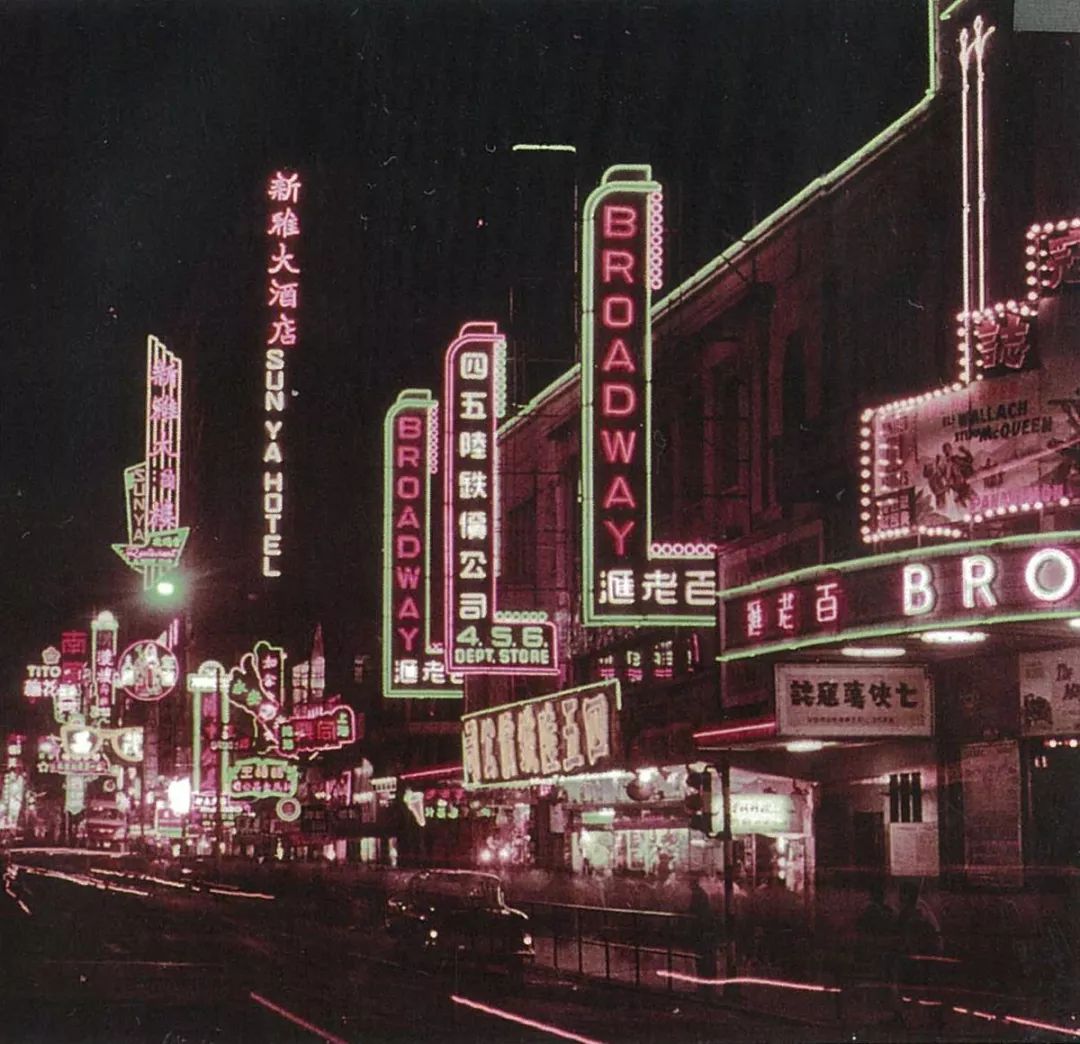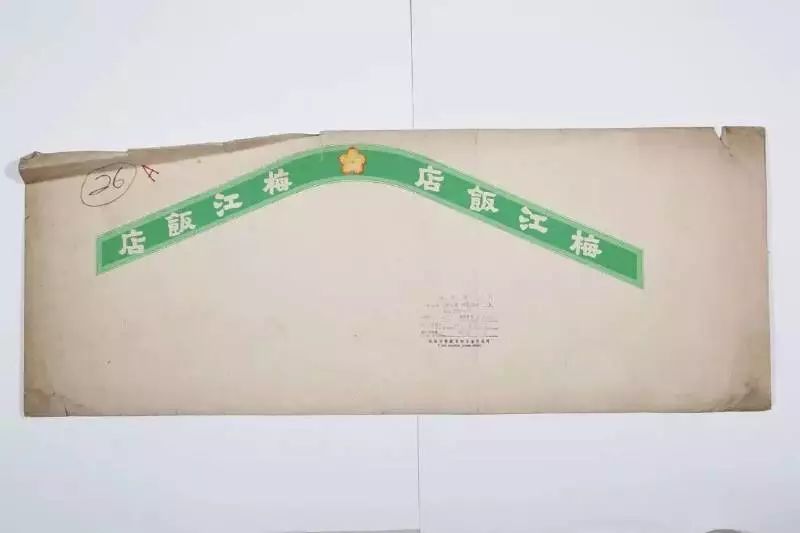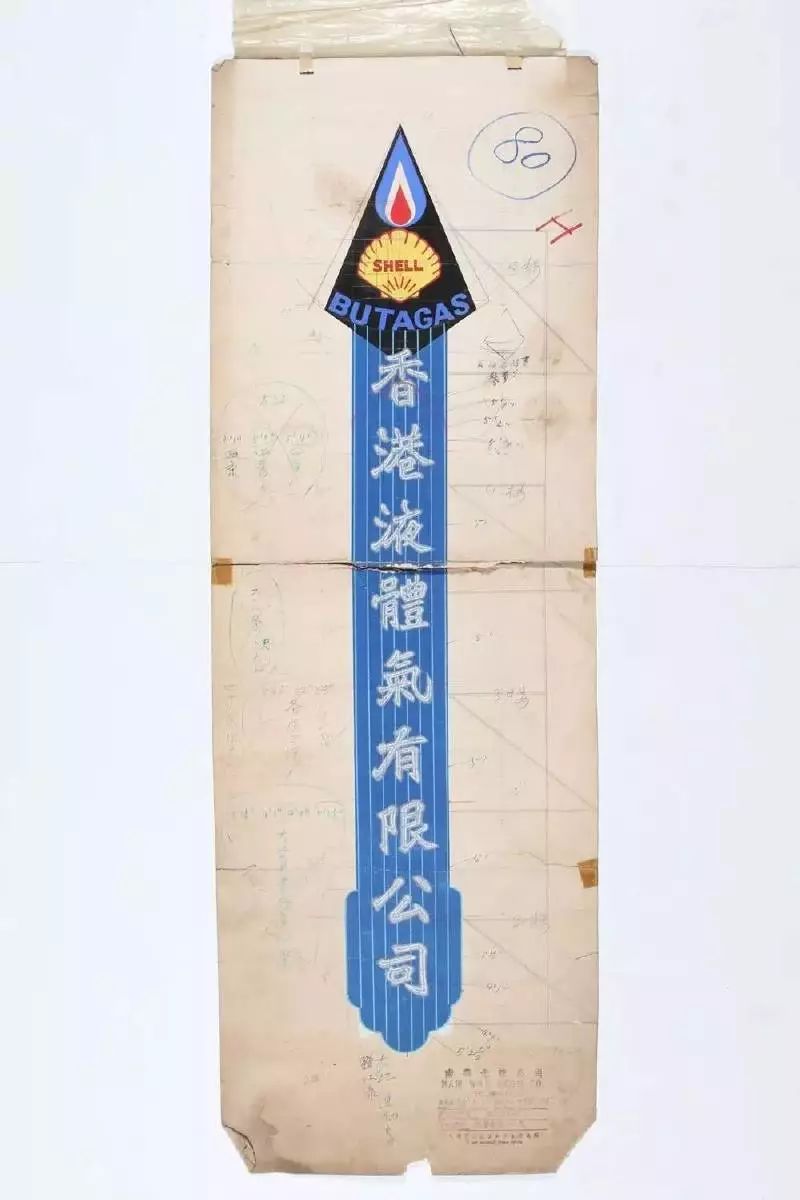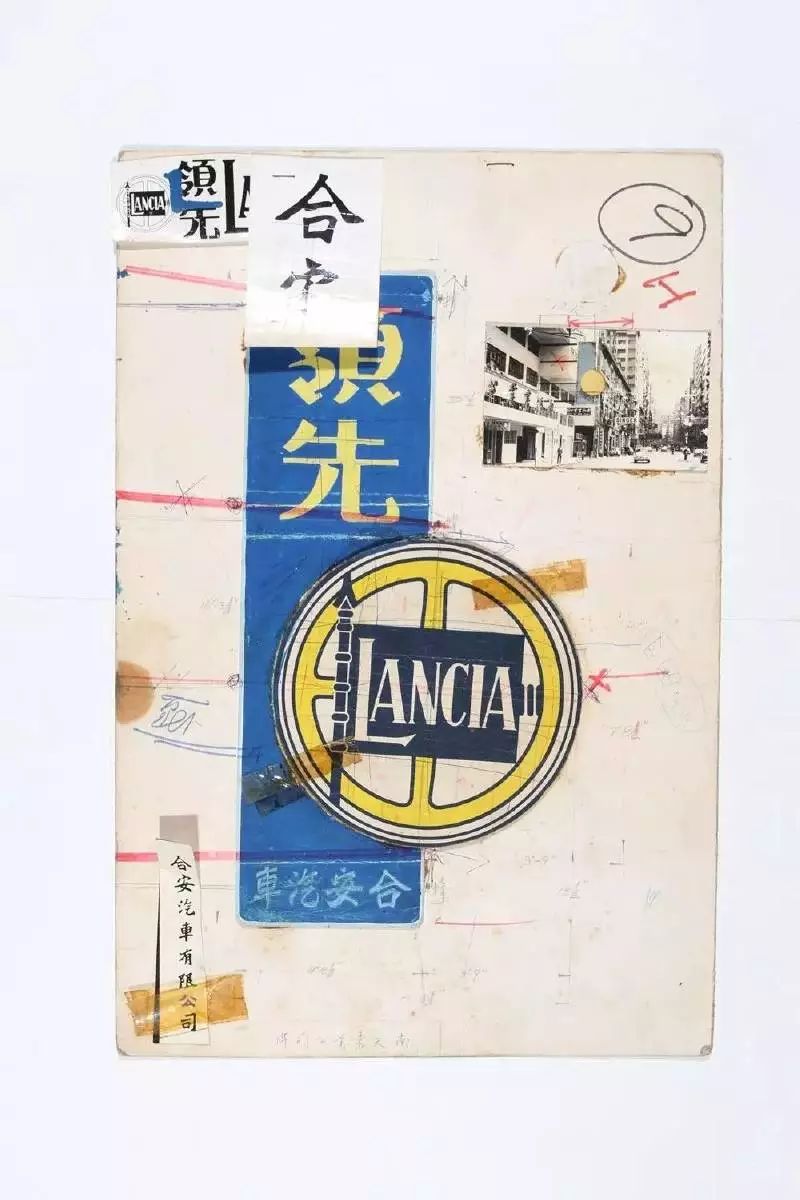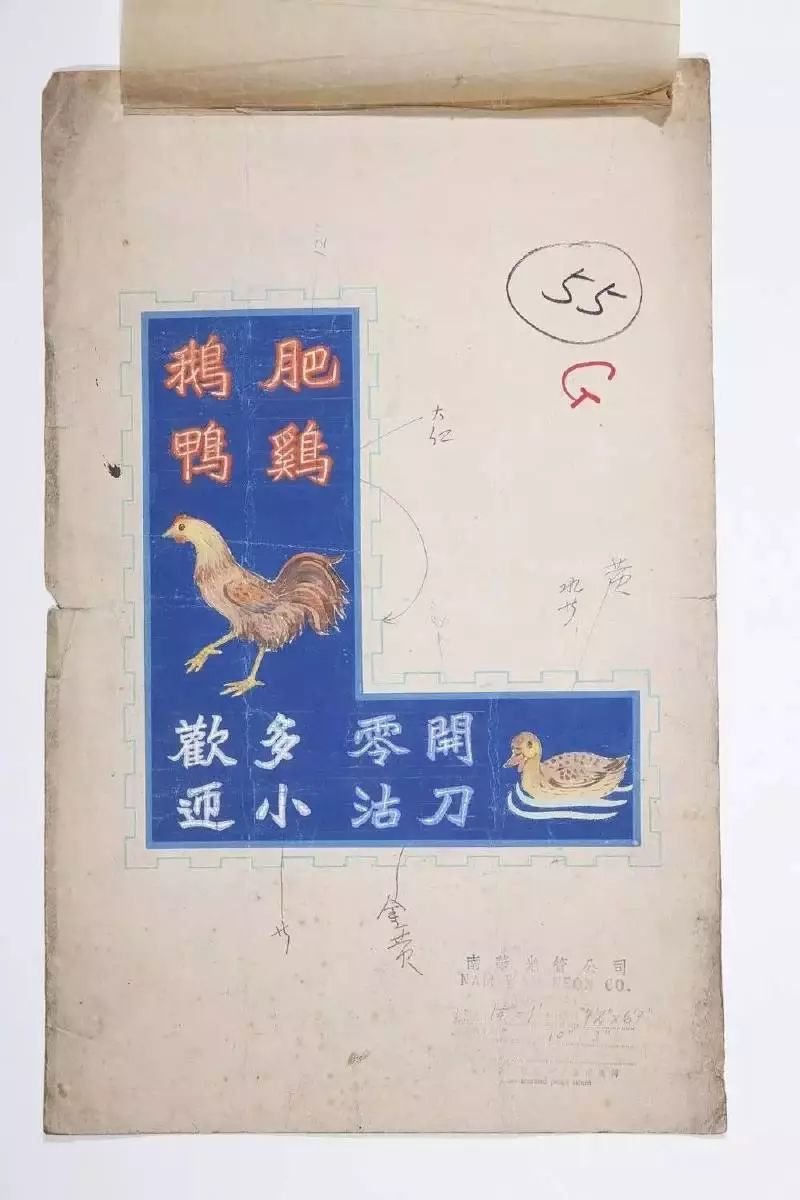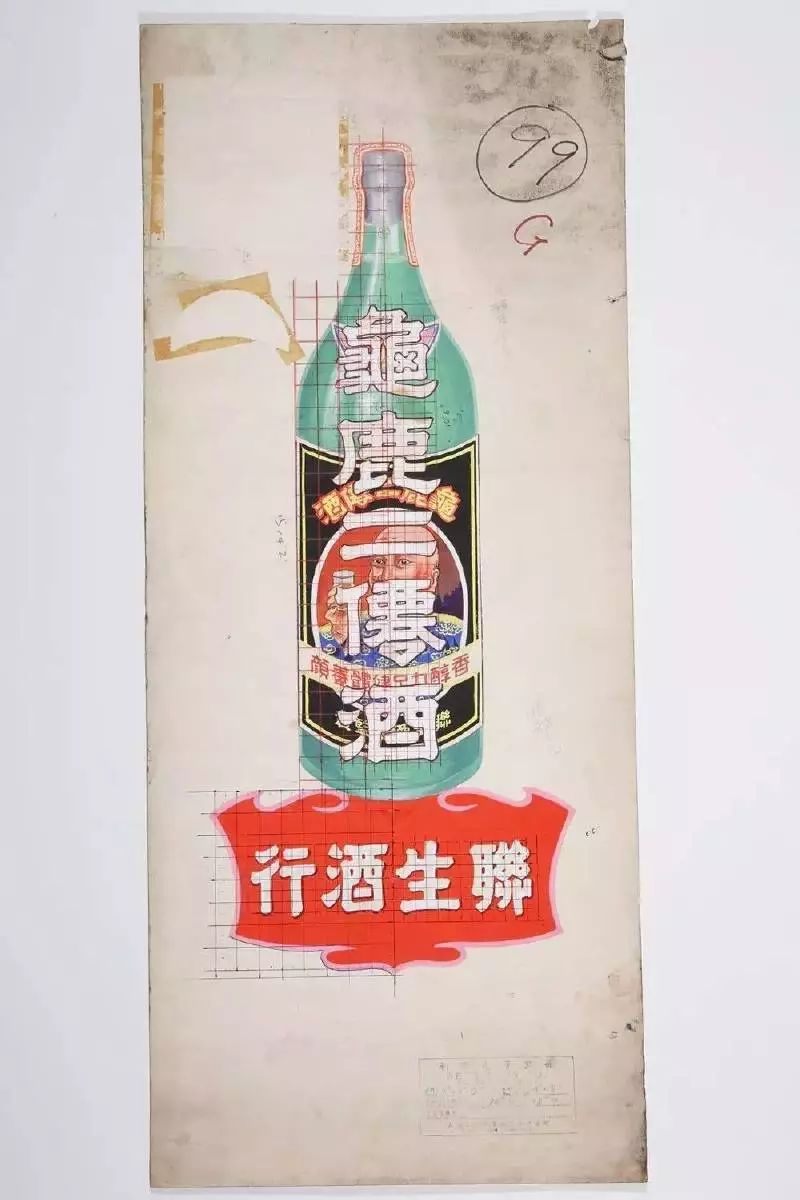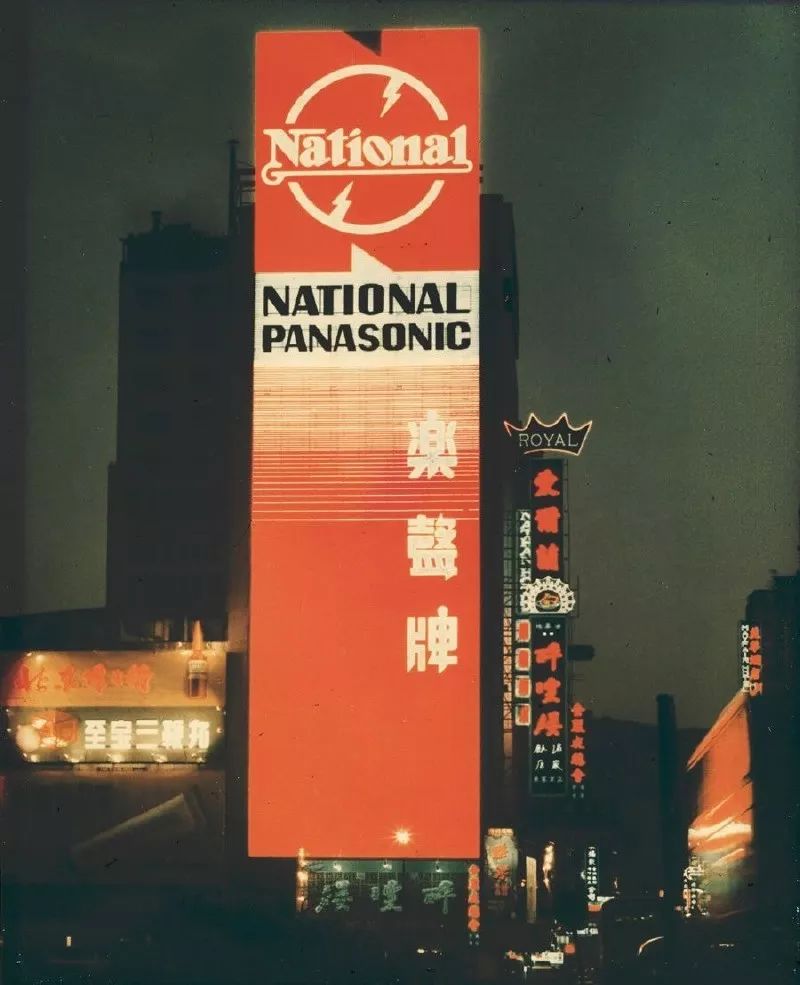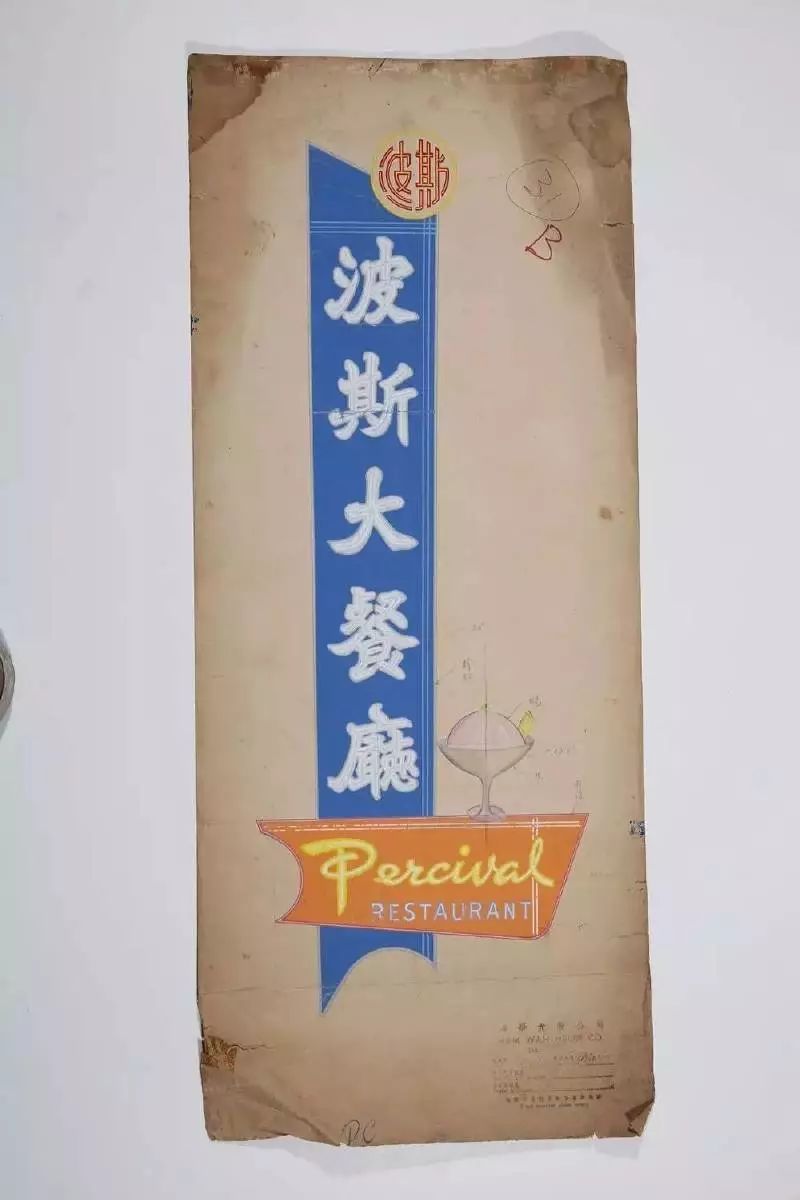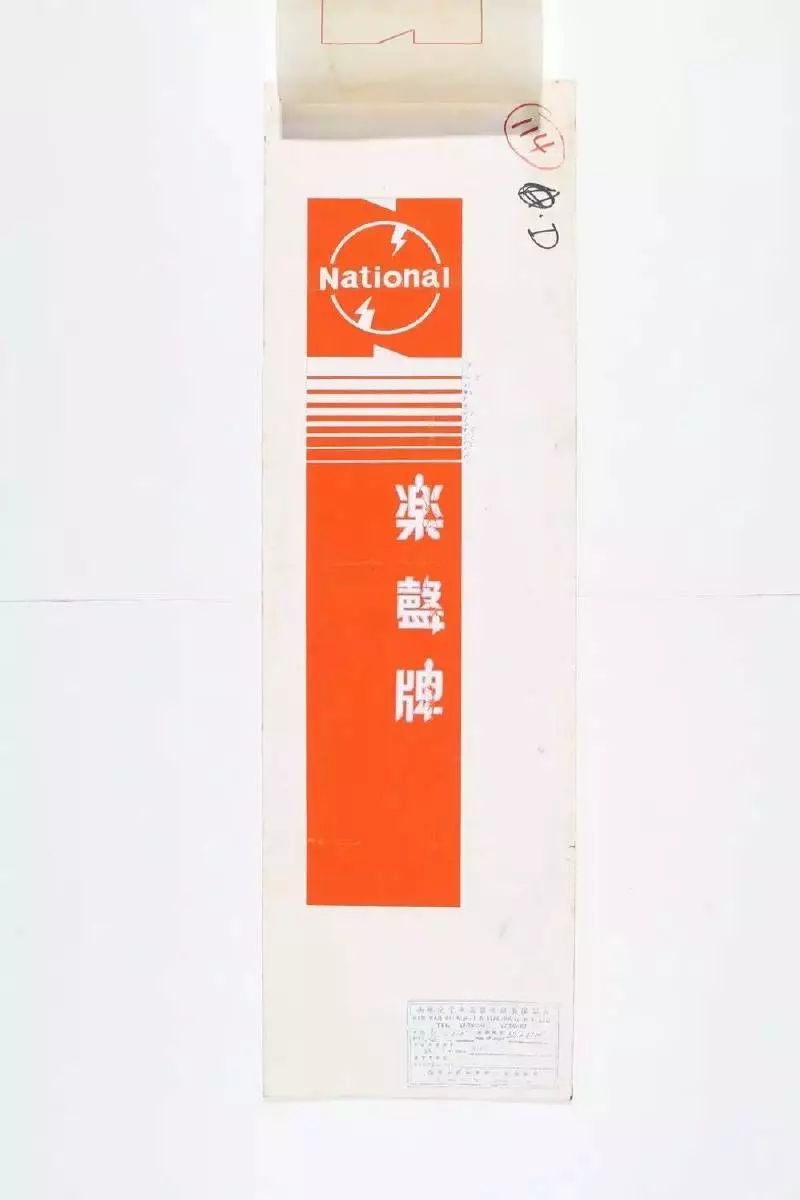
手工年代,前辈们的霓虹灯广告这样制作
霓虹灯作为户外广告的重要表现形式,是一件在中国迅速获得中文名称的西方舶来品。它结合了古代中国的书法艺术和现代广告技术──如今,霓虹灯在香港,虽然不断减少,但已成为了香港的象征。从香港与霓虹灯的文化,香港政府与民众对待它的态度中,我们从中又可以学到哪些?
想知道一座城市有多繁荣,要看它入夜后有多光亮。自上世纪50年代起,“东方之珠”的称谓就成为了香港的代名词,而“香港繁荣靠设计”的说法,讲的就是香港街道上字体各异、色彩斑斓的霓虹灯。
霓虹灯曾是户外广告的主要形式之一,具有很强的装饰性,可以为夜幕增加色彩和动感。因其制作特性,故多以字体的形态出现。
下面我们就来看看在手工年代,那些香港的广告前辈们,他们在制作霓虹灯广告的设计稿。
这一块乐声牌霓虹灯,因其面积大,且位置比较好,给人留下了深刻的印象
它的制作稿是这样的:
接下来是新全记面店:
新全记面店
银龙舞厅
蓝宝彩色电视
艺宫摄影
骆驼漆
梅江饭店
香港液体气有限公司
领先汽车
肥鸡鸭鹅
泉章居金牌盐焗肥鸡
杏花别墅
龟鹿二仙酒
嘉士伯啤酒
怡安泰洋服呢绒
嘉顿餐厅
松柏宝石屋
波斯大餐厅
京华公寓
香港民众对于周边霓虹灯早已像熟悉空气般亲切,伴随着霓虹灯逐渐退出历史舞台的步伐一起的,还有香港民众的怀旧情绪。对于霓虹灯文化的纪录片、展览不断在香港展出,从视觉文化和艺术角度探讨霓虹在香港的生存空间。
当我们提起香港与霓虹灯的视觉文化,最先想到的便是霓虹招牌。霓虹灯的簇拥应和香港的璀璨,霓虹灯就是香港的视觉标签。